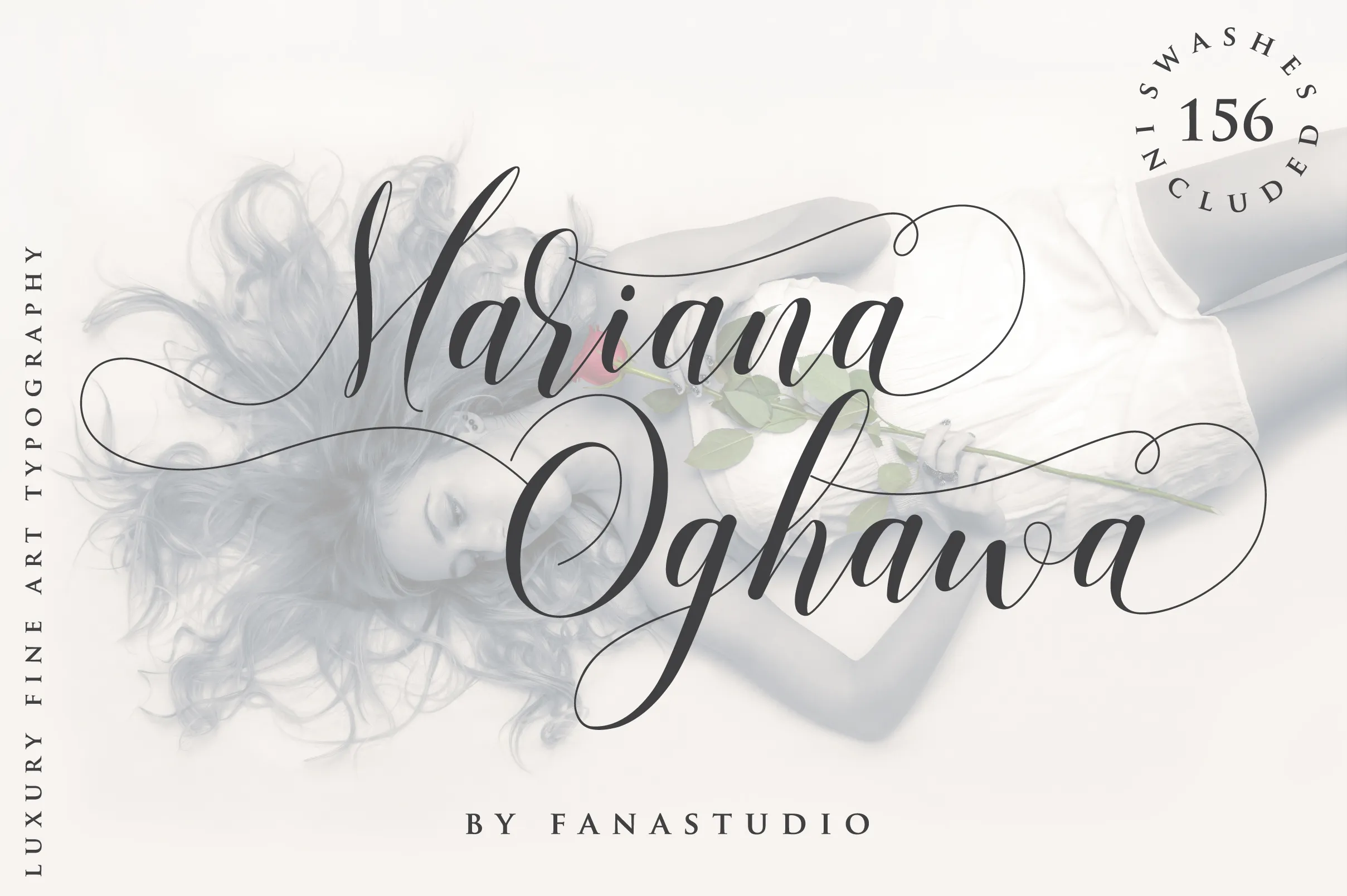
Mariana Oghawa Script Font – Download Grátis
Aqui está uma versão em português para a descrição solicitada da fonte ‘Mariana Oghawa Script Font’: ‘Sofisticada e moderna, Mariana Oghawa é uma tipografia de calligrafia que traz um toque elegante e único. Esta linda fonte script oferece um toque pessoal para seus próximos projetos de arte. Perfeita tanto para logos e identidade visual quanto para convites, material de decoração, design de casamentos ou postagens nas redes sociais, Mariana Oghawa proporciona uma aparência moderna e elegante que se encaixa em múltiplos tipos de projetos. Adaptable e versátil, a Mariana Oghawa é ideal para criar um toque único em diversos campos. Seja um post na rede social, embalagem ou marcadores de produto, você pode transformar essas criações com sua personalidade própria através do uso desta fonte script. Essa opção permite que seus projetos se destacuem, combinando os elementos modernos e elegantes da Mariana Oghawa para um visual único. Quer seja para as etiquetas em embalagens de produto ou um desenho fotográfico, a Mariana Oghawa sempre dará uma sensação profissional. Ela é uma excelente opção para qualquer projeto que precise de um toque de escrita artesanal.’